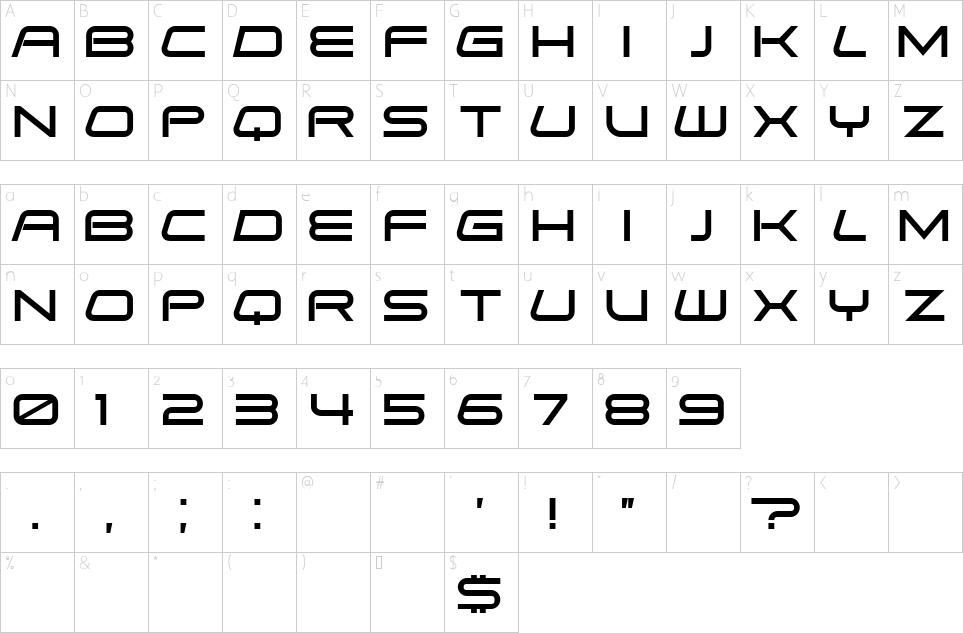
A fonte Declaration é uma elegante escolha para quem procura uma face sóbria e firme para publicações importantes ou documentos formais. Desenvolvida pelo designer Vladimir Nikolic, esta fonte já foi baixada 356 vezes. Com um estilo assertivo que se destaca em espaços de trabalho profissional, a Declaration oferece uma solução perfeita para aqueles procurando uma face única e confiável. Perfeita para assinaturas firmes, gráficos importantes ou qualquer outro documento formal que exige uma presença forte e distinta. Download agora para adicionar um toque especial à sua próxima publicação escrita.